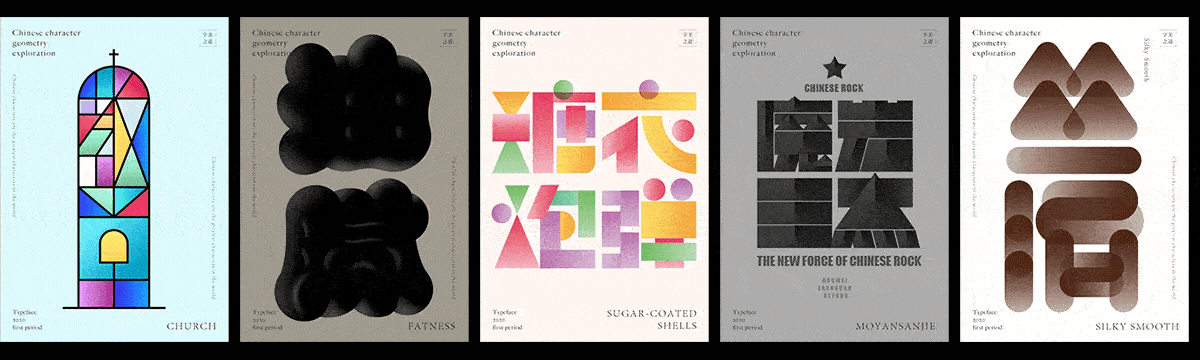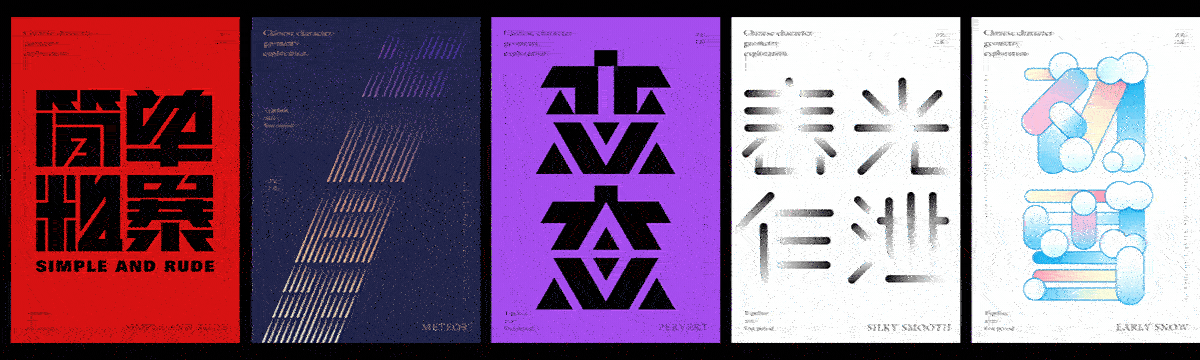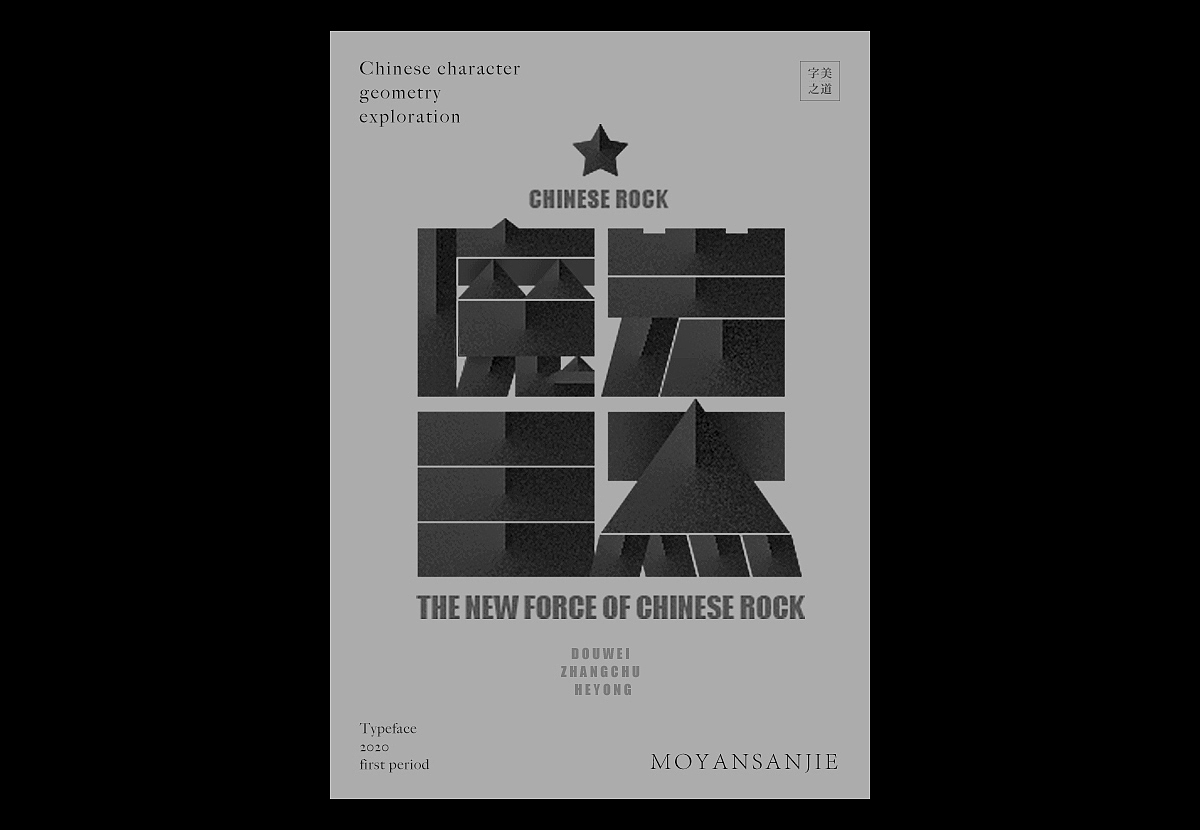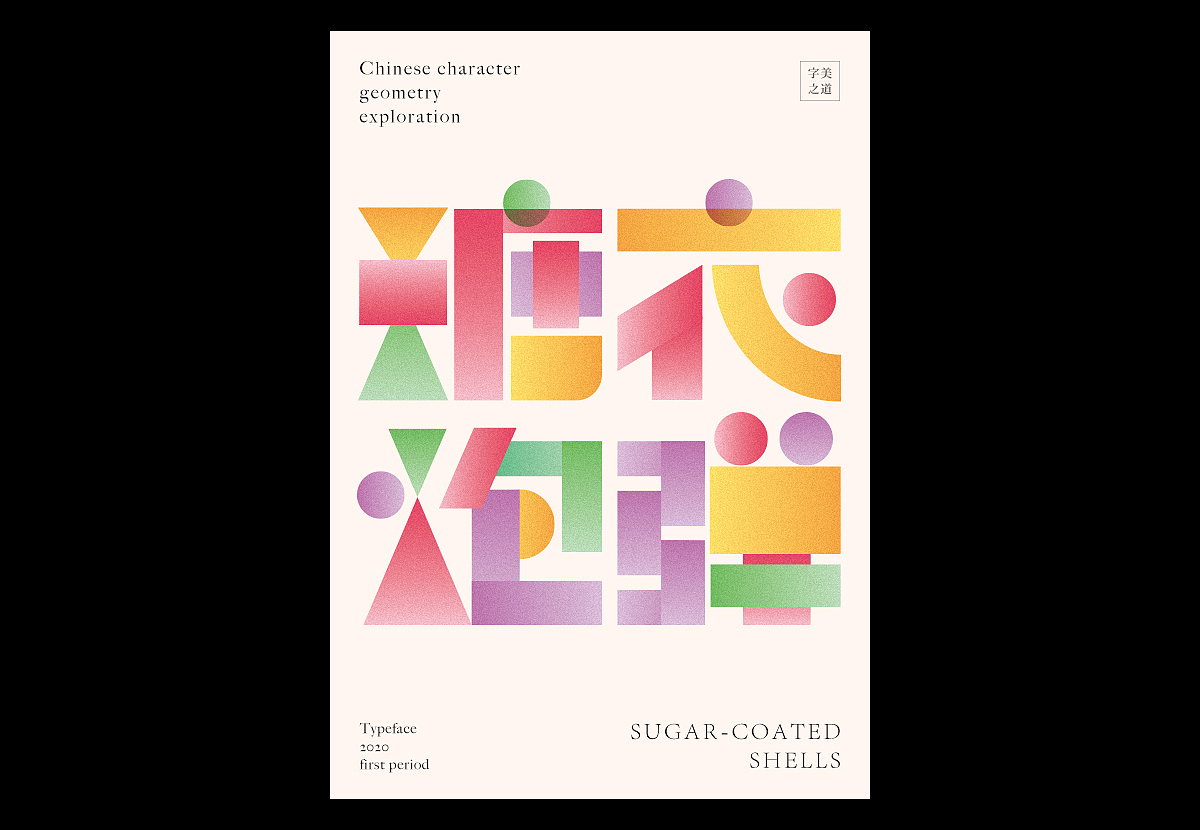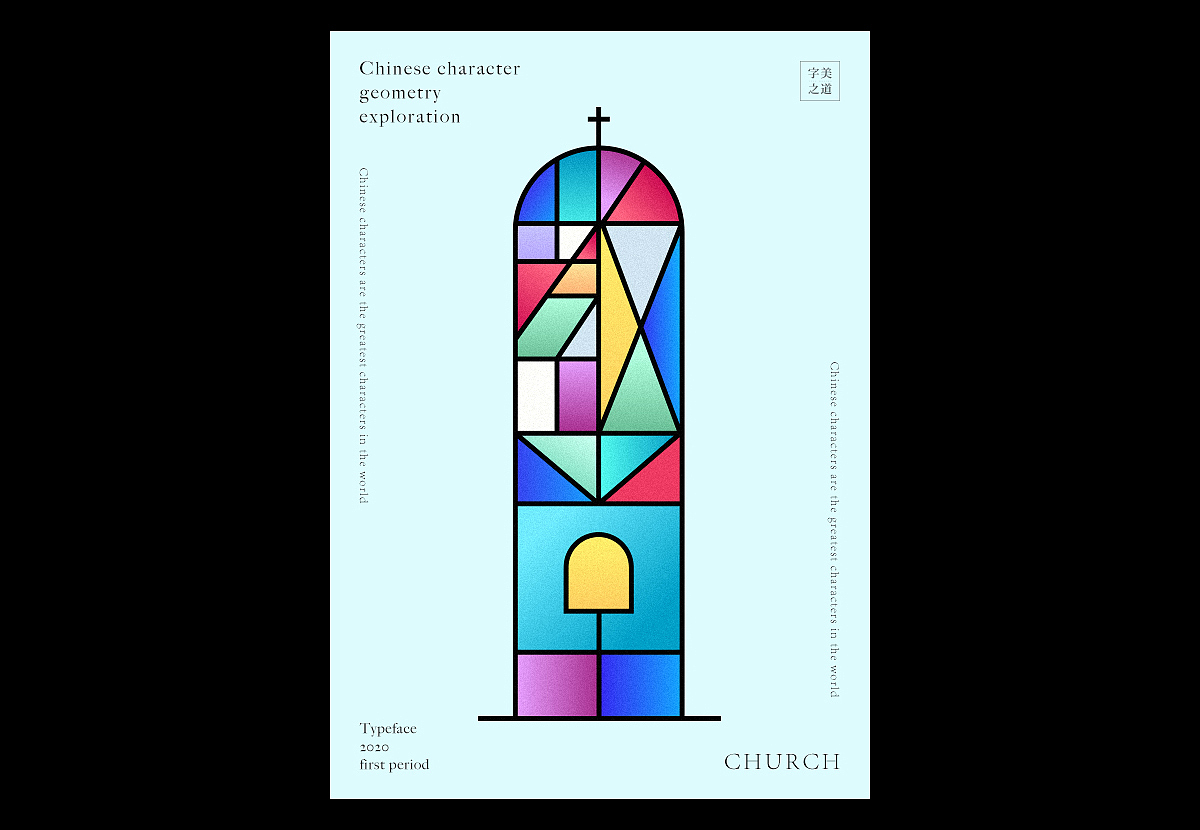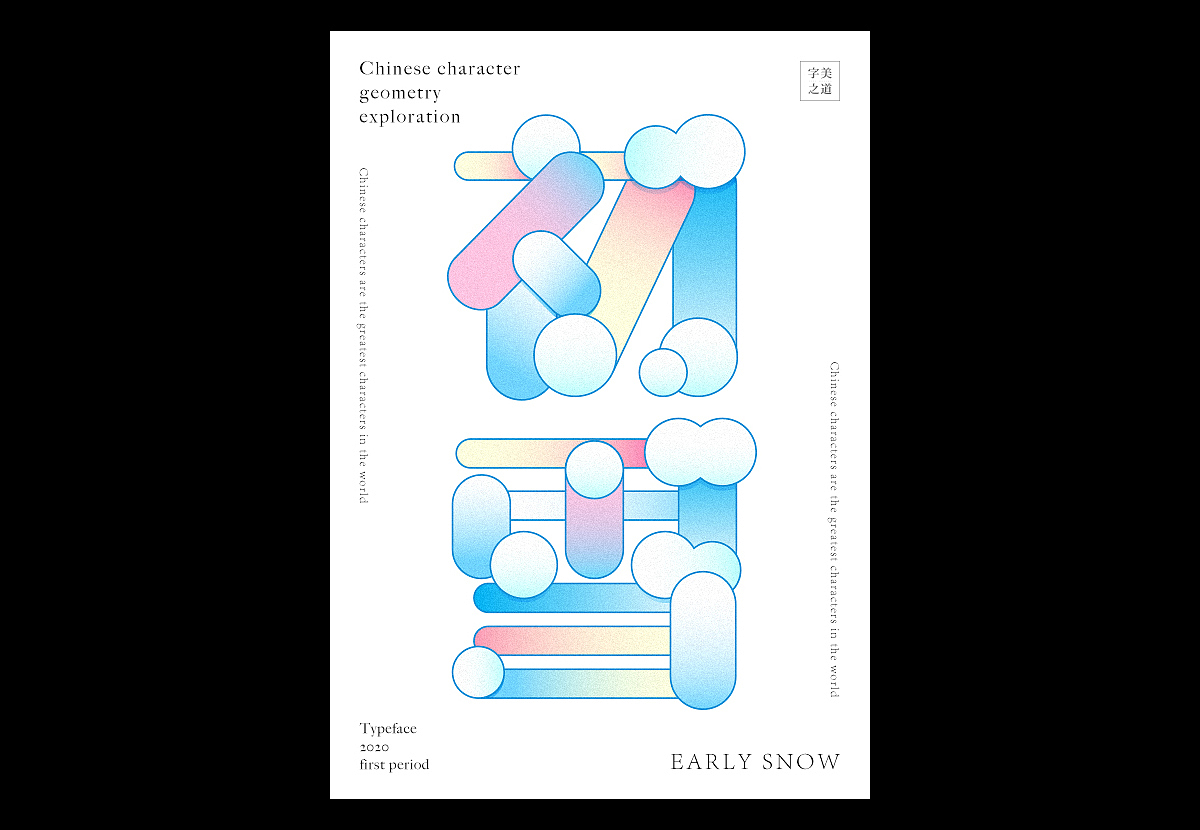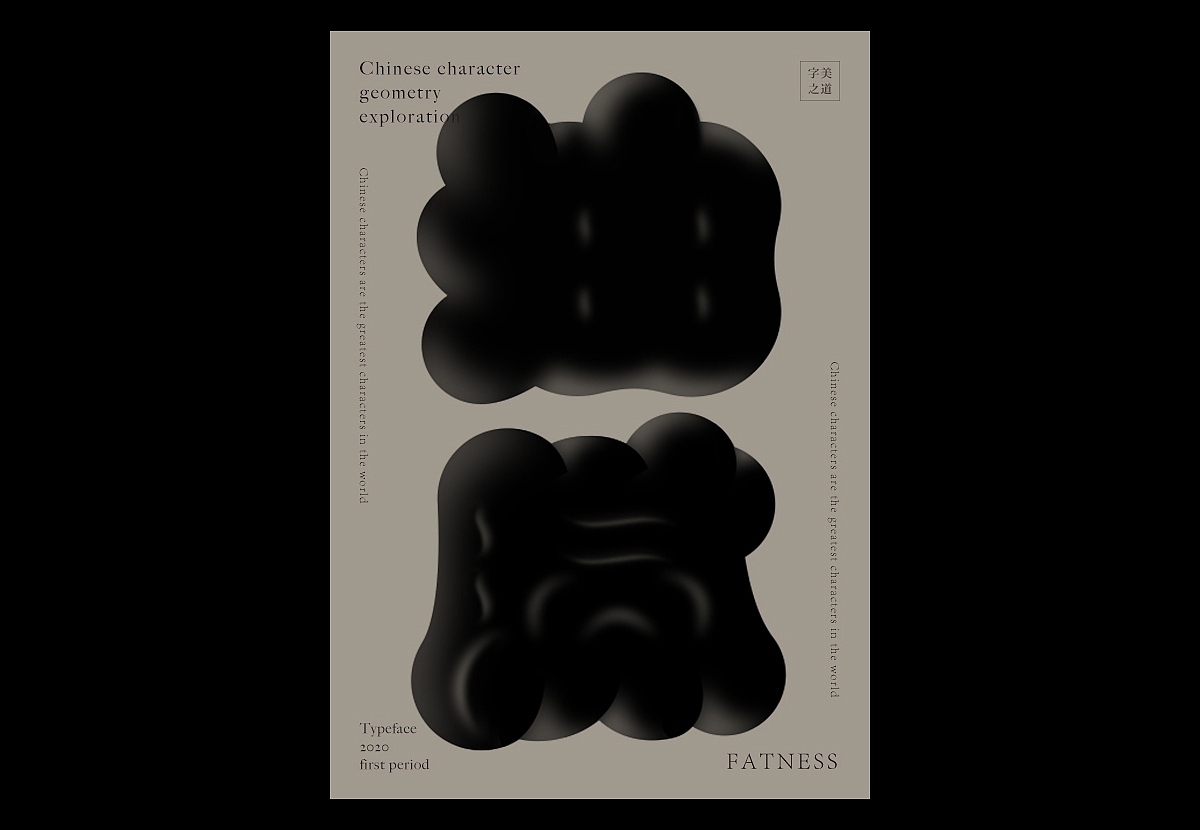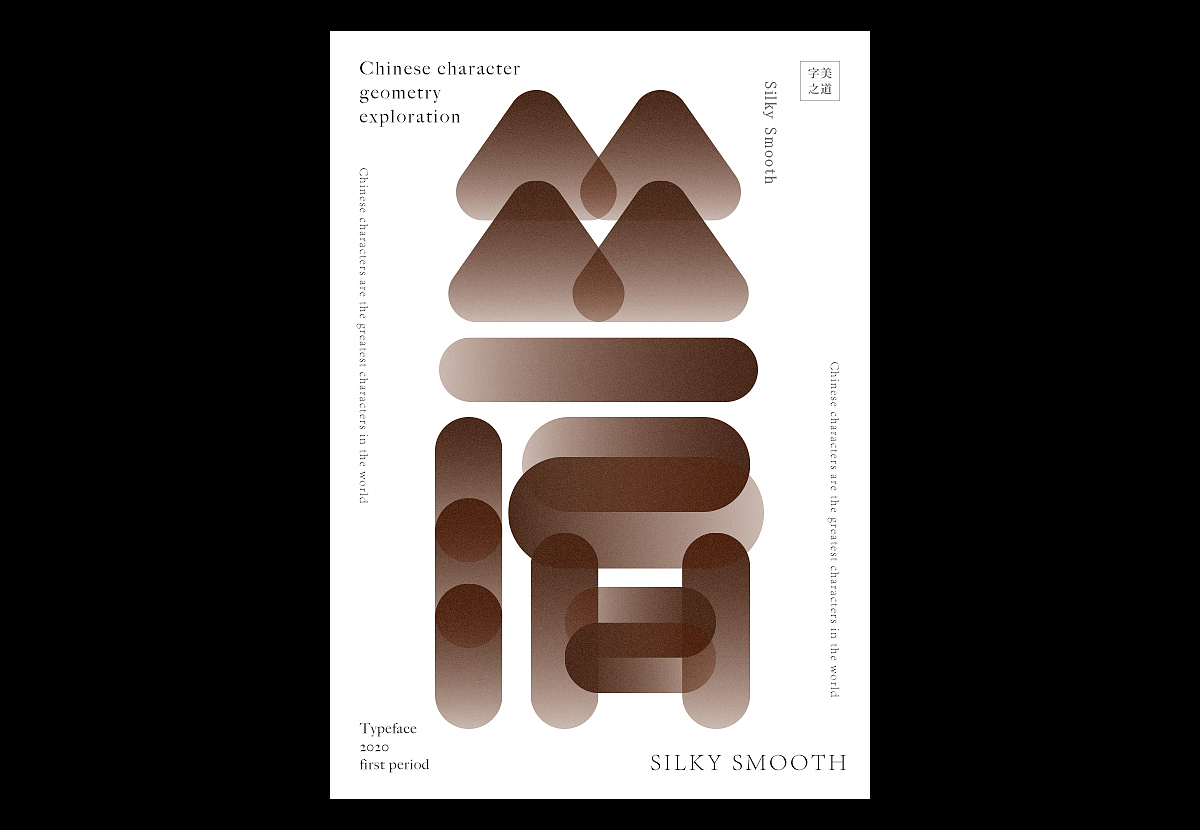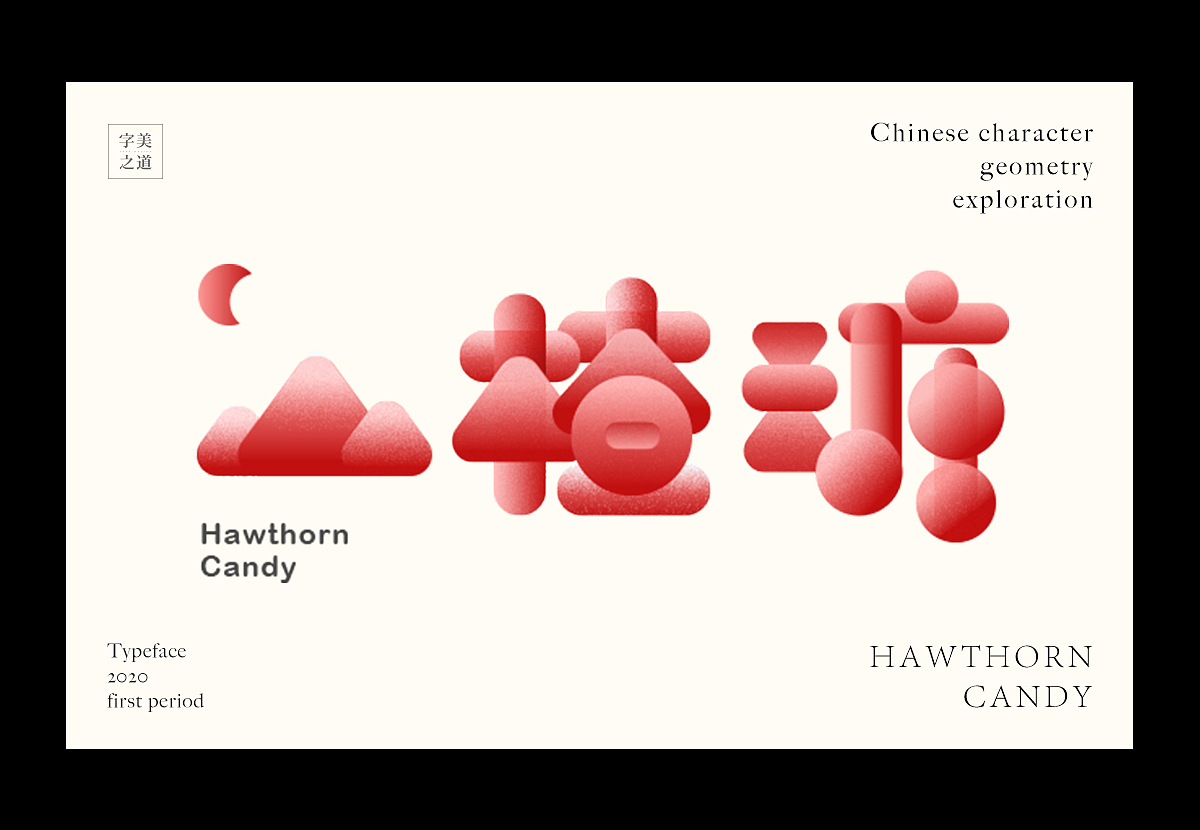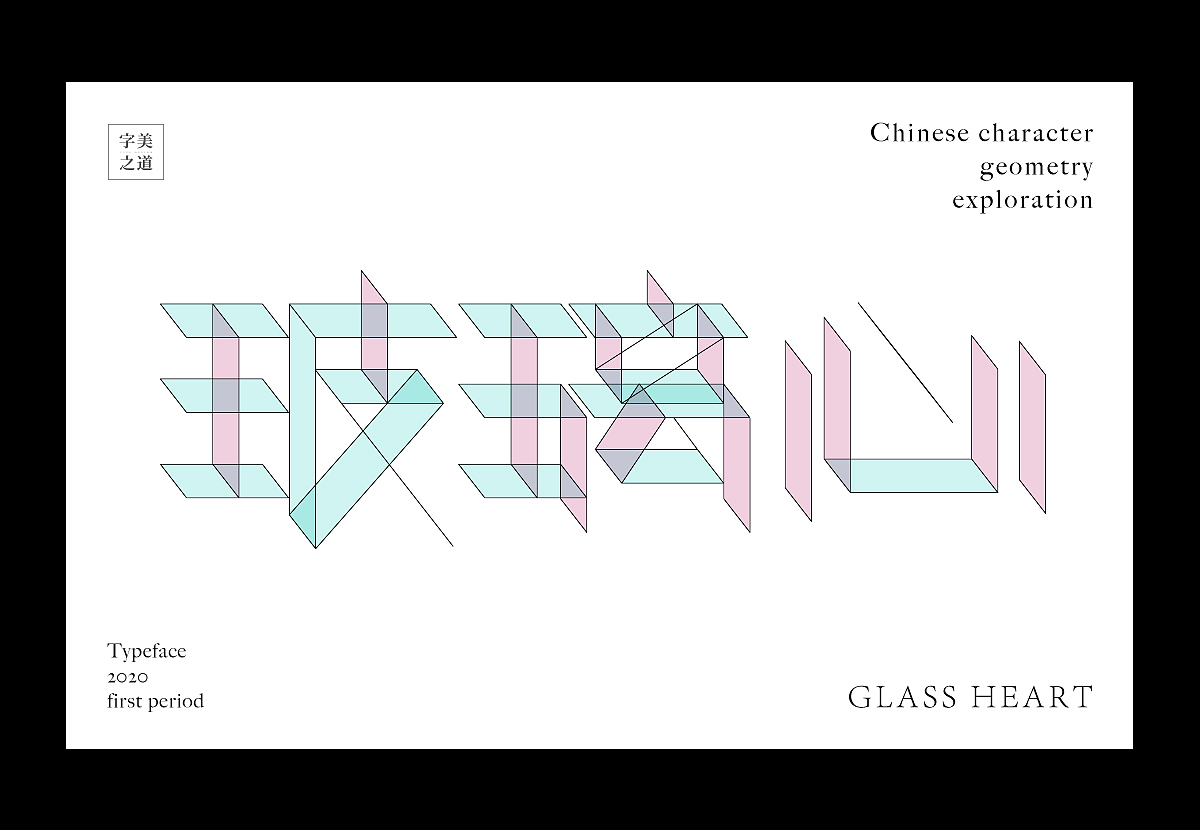
汉字几何的可能性
从包豪斯时期开始,先驱设计师们就尝试将字体进行几何化的处理,直到今天,几何化依然是字体设计的重要思路之一,本期探索将字体最大限度的几何化,运用恰当的几何形式去表达字体本身的含义。
魔岩三杰 - 中国摇滚辉煌岁月
这有些简单,这有些粗暴,这有些让人受不了
我想知道,流星能飞多久
糖衣炮弹,疯狂的向我开炮吧!
教堂,色彩斑斓的印象
初雪,融化了你和我的心
油腻,人到中年,难免油腻
来吧,我们一起纵享丝滑
好变态,不过我喜欢~
原来寂寞的时候,所有人都一样。- 春光乍泄
山楂糖,酸到上头,甜到忧伤
做人不能太玻璃心
就是他,一个不懂球的胖子
猫吃鱼,狗吃肉,奥特曼呢?
于是乎,就有了怪兽历险记
这世界多一个人笑,就少一个哭。- 煎饼侠
来自火星的鸡,开飞碟来的
这是我们自己创造的世界,却分不清真和假了。- 盗梦空间
门前有座山,山里有个院儿